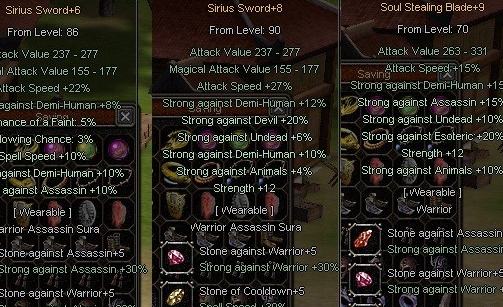
Nazwa czcionki z SG :D
Nie wiem czy dobrze mówię.. ale.. Tahoma ?
To nie jest zwykły arial czasem?
arial jest bodajże na PLu i tak nie wygląda
chyba że jakiś inny rozmiar czy coś
hahah działa! To arial 14!